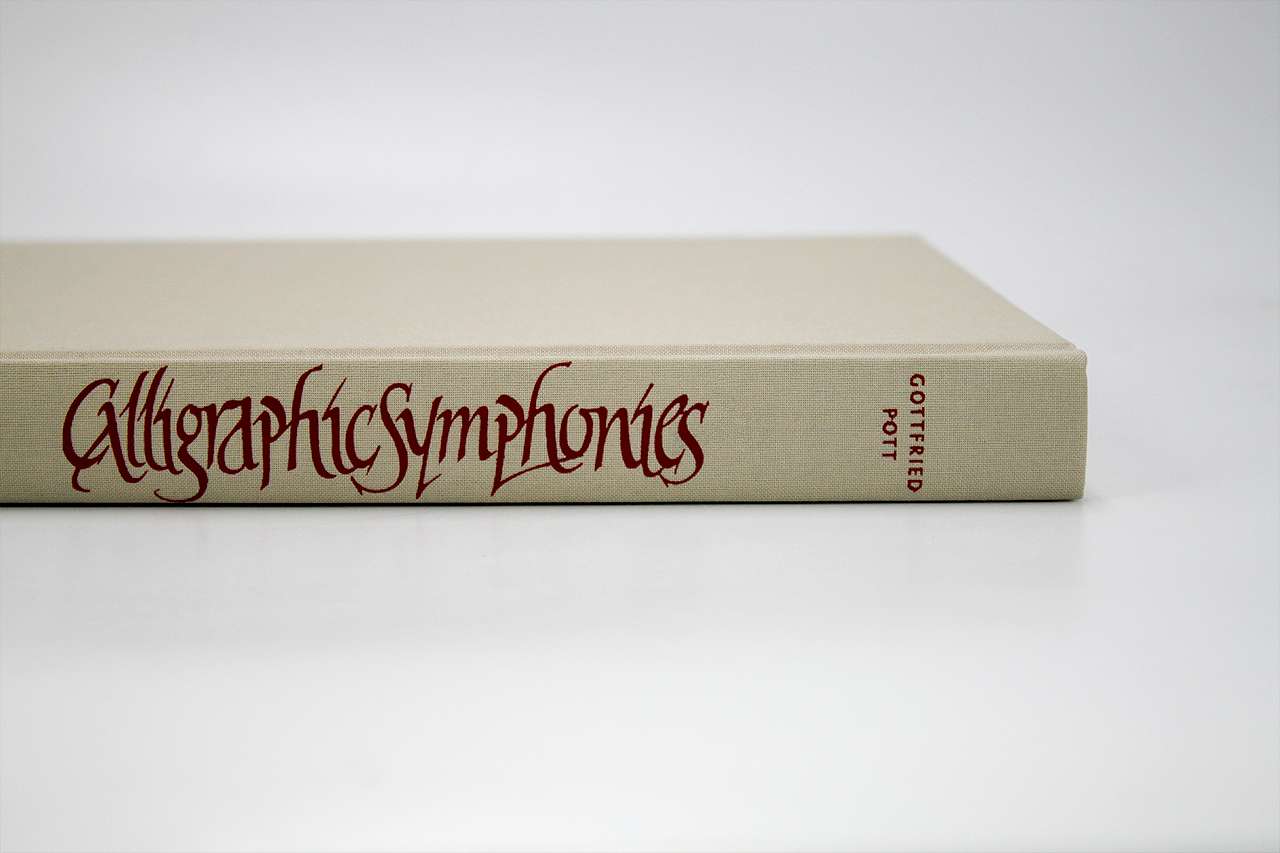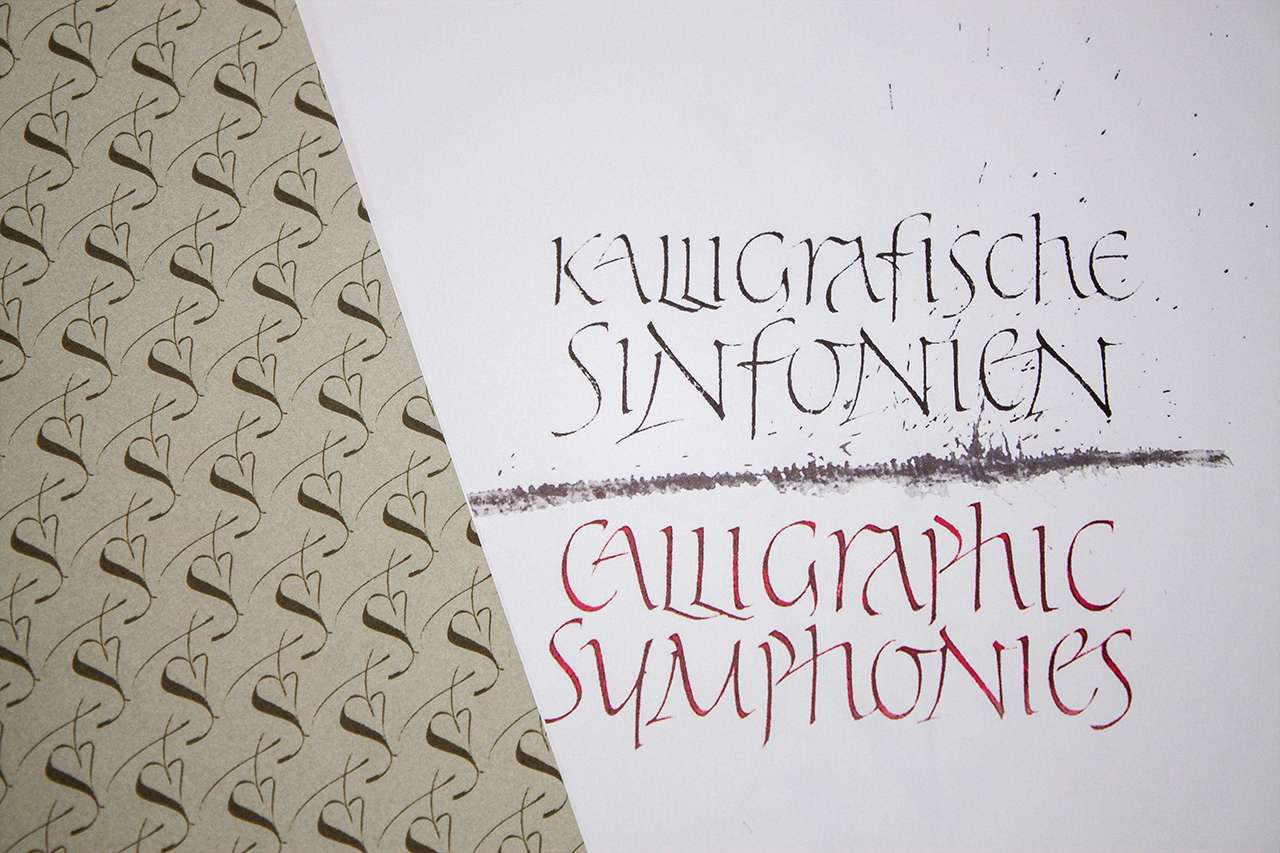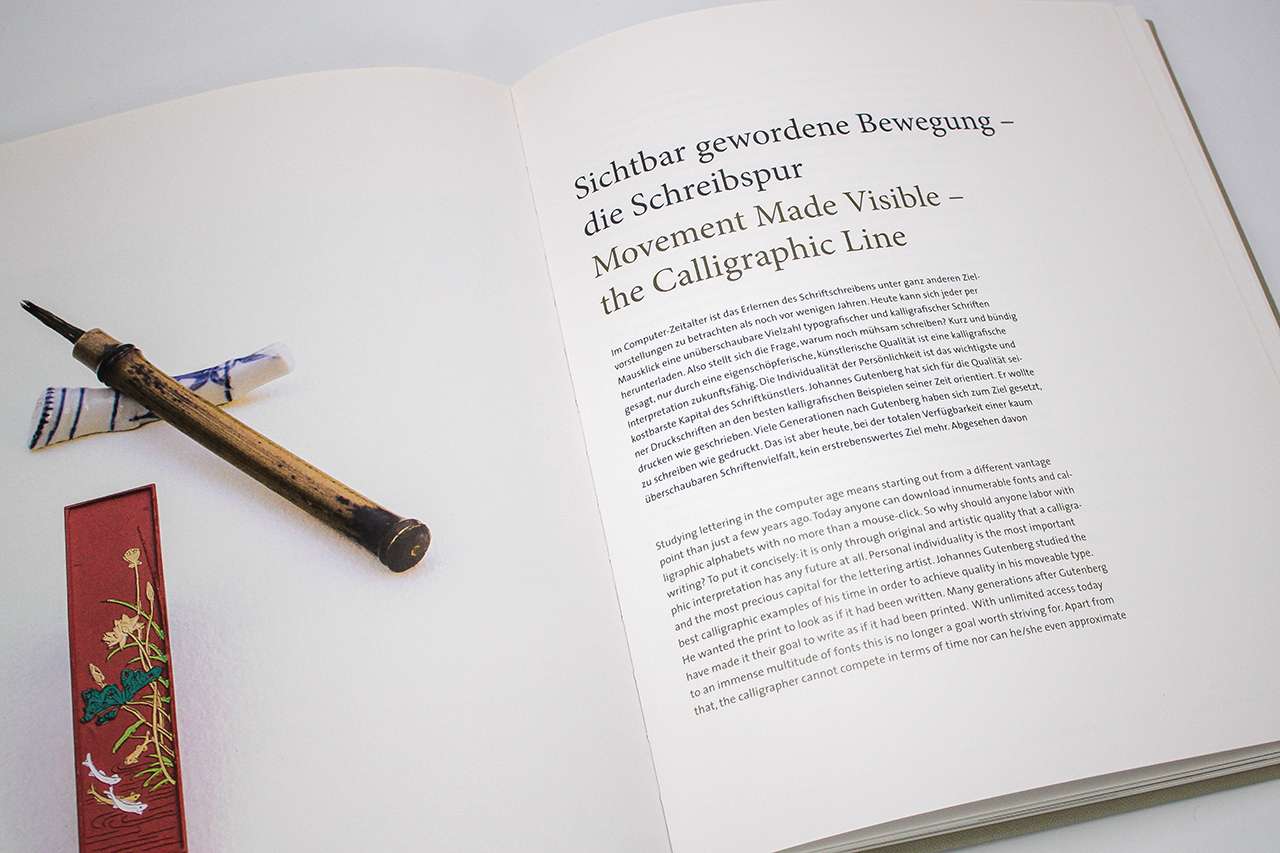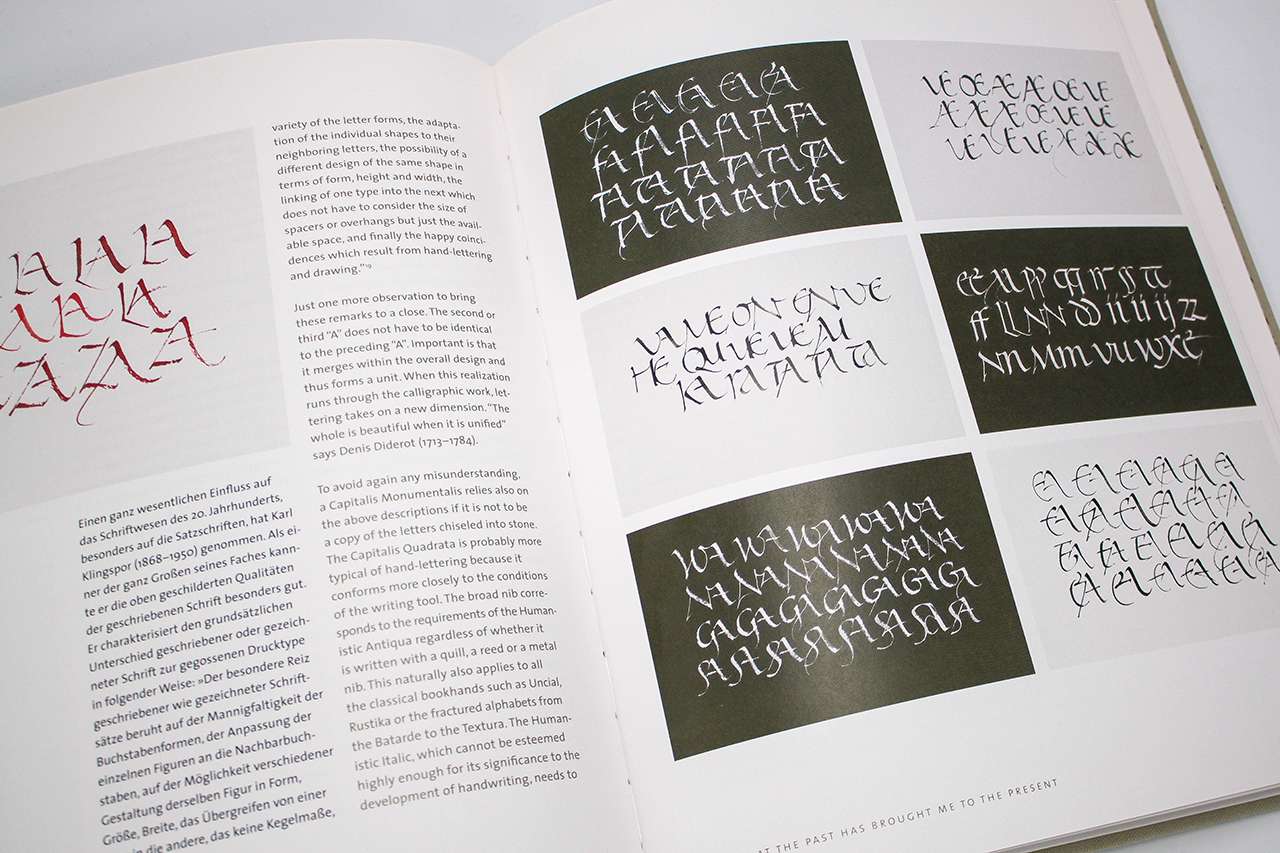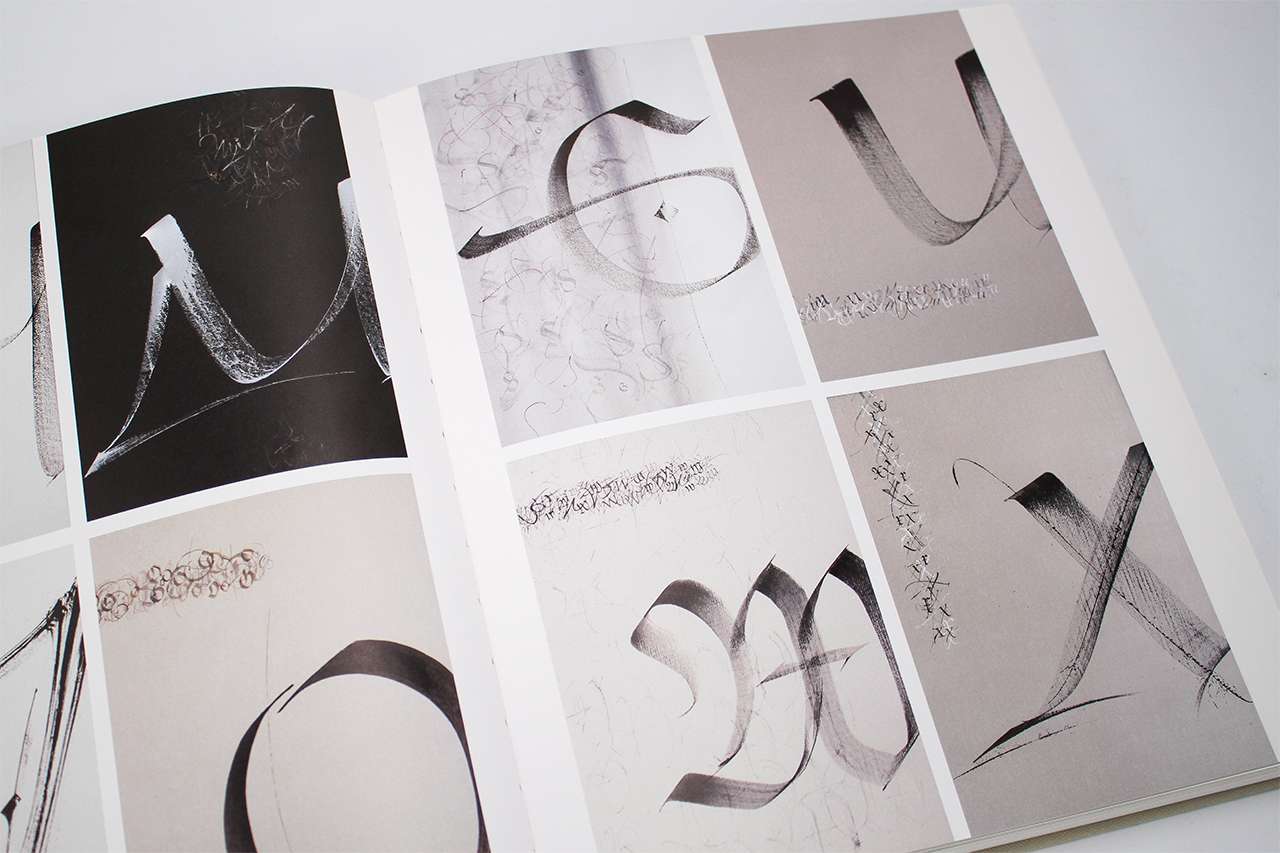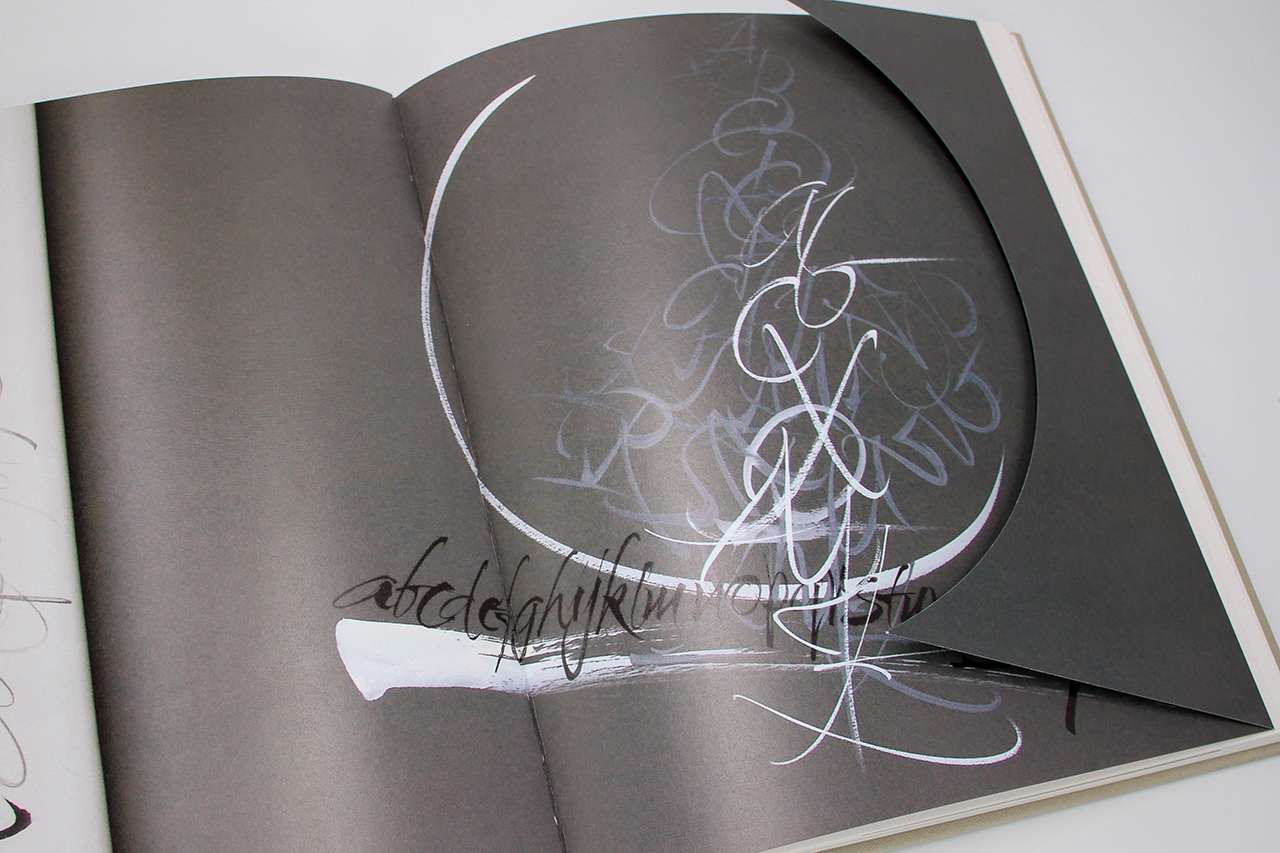
Kalligrafie ist sichtbar gemachte Musik.
Gottfried Pott komponiert Fugen aus Buchstaben. Stimmen Sie ein in seine kalligrafischen Sinfonien! Lernen Sie die visuellen Kompositionen aus seinem Schreibmeisterbuch kennen. Lauschen Sie ihm, wie er – ganz im Einklang mit sich – sich selbst vergisst.
Vielleicht hören Sie dabei auch in sich hinein. Denn Kalligrafie ist visuelle Meditation, Spiegel der eigenen Stimmungen. Die Schreibspur ist sichtbar gemachte Bewegung. Diese Spur bleibt über die Entspannung hinaus – vielleicht ist Kalligrafie das neue Yoga …
Entdecken Sie Harmonie und Rhythmus von Texten neu. Und stimmen Sie ein in die 26 kalligrafischen Sinfonien, in denen Gottfried Pott den »Sound of Type« einfängt.
Im Gegensatz zu seinen Kalligrafie-Workshops in Buchform ging es Pott hier nicht um Didaktik und Heranführung. Hier zeigt der Meister, was er kann. Ein Fest der Kalligrafie, eine Augenweide, man meint beim Betrachten die Berliner Symphoniker live zu hören!
Kalligrafische Sinfonien